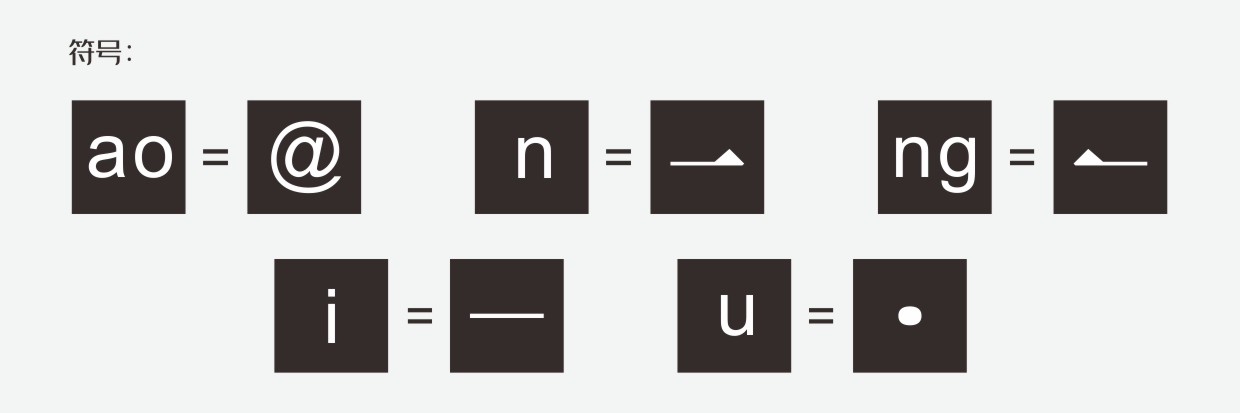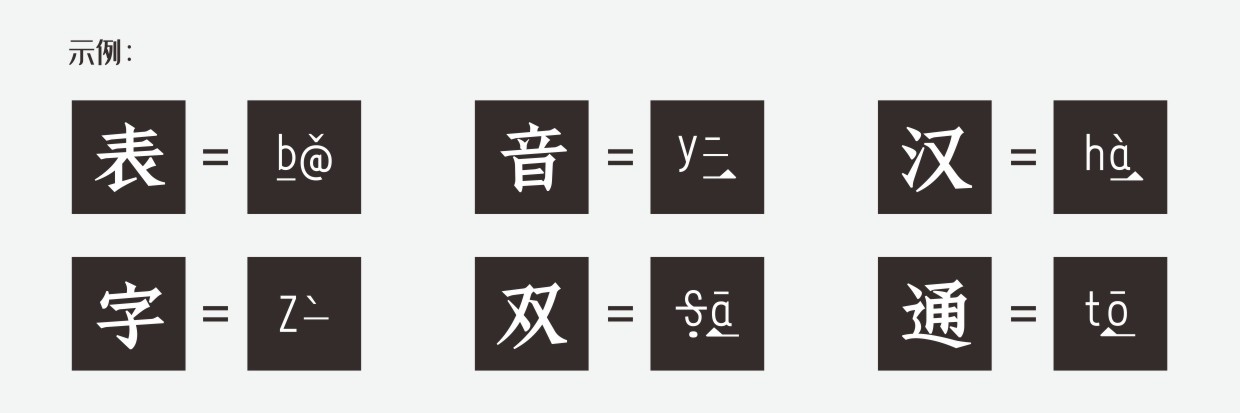
拼音新玩法-定制字体
表音汉字体-一种拼音的新玩法!
吉页字库为南京中桥兴定制开发了一款“表音汉字体”。表音汉字是中桥兴的创始人季先生经过多年研发的一款输入法(双通输入法),为此委托吉页字库为其定制一款表音汉字注音的字体。因该字体为开放下载字体,汉字部分客户选用了思源黑,吉页字库仅为字体注音设计开发(包括多音字,共6个字体文件,可揽选某个多音字,在6个字体中选择需要的读音)。因客户想要单字接近正方形,故汉字部分进行了压扁处理。
表音汉字的拼音是这样拼写的:
声母除了zh、ch、sh有变化,其它不变,韵母中用到三个字母a、e、o及@、→、←、―、·符号。
aeo代表的还是原读音,那么表音汉字的拼音是怎么个拼法呢?下面我们就来分解一下。
有没有看出来,新玩法只占两个字符位。了解了表音汉字的拼写方法后,我们再来看一下注音后的字体吧。
是不是很好玩,鸡哥在最初接触的时候,只看了几眼就明白了表音汉字新玩法的方法,感觉比小时候学拼音简单多了。只是鸡哥小学没学好,语文老师自己都不说普通话,所以到目前为止,都分不清舌前音和舌后音分别都是哪些字。老家话总爱带上儿化音,什么门、闷、安、爱、本、呗、带、单等等,根本搞不清记不住。或许是因为学过了拼音才觉得这个简单,亦或许是此方法确实容易理解,不管怎么说,这是对拼音及输入法又迈向了新的一个起点,未来,或许会由此启发人们研究出其它好玩的拼音及输入法。